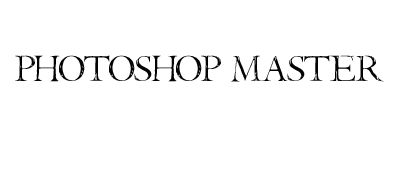
жаль, что нет поддержки русского языка.
великолепный, спасибо)
Красивый шрифт, очень понравился!
Очень изящный шрифт.
нормаль нормальный такой)
хороший шрифт